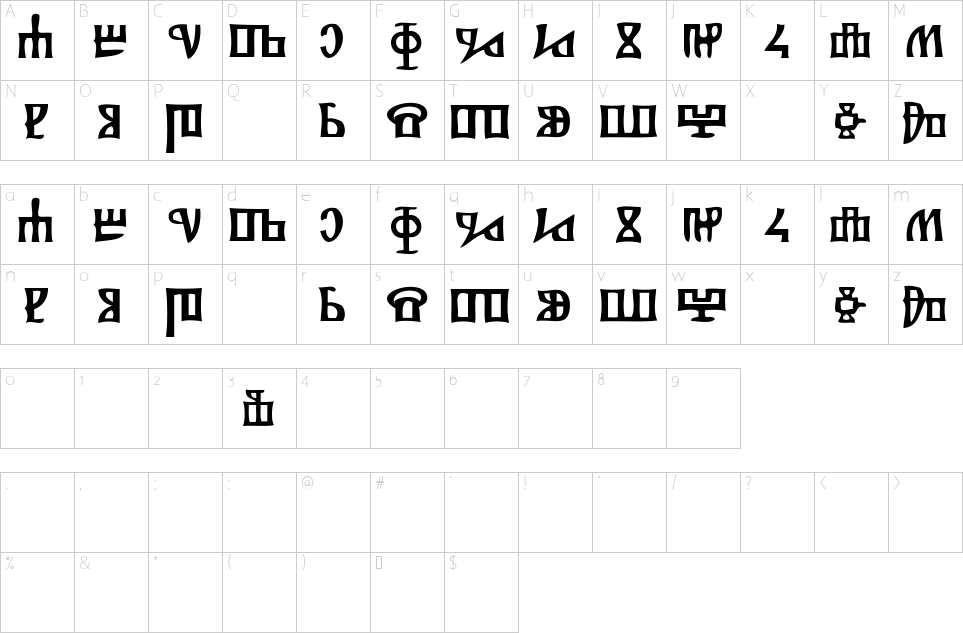
A Glagolitsa Font é uma beleza de fontes que destaca sua rica herança eslava na sua escrita antiga. Desenvolvida pelo designer Daniel Weru, esta elegante fonte garante um estilo autêntico e sofisticado para qualquer projeto. Se você está procurando por um texto agradável e único, não há dúvida de que Glagolitsa é uma opção sólida. Sua simplicidade e beleza combinam perfeitamente com a riqueza dos textos da sua página web ou aplicativo, tornando-a uma escolha ideal para designers gráficos e escritores. Em um ano desde o seu lançamento, Glagolitsa foi baixada mais de seis mil vezes pelo mundo inteiro, demonstrando seu valor como fonte. Descubra por si mesmo as delícias desta fonte única e elegante.